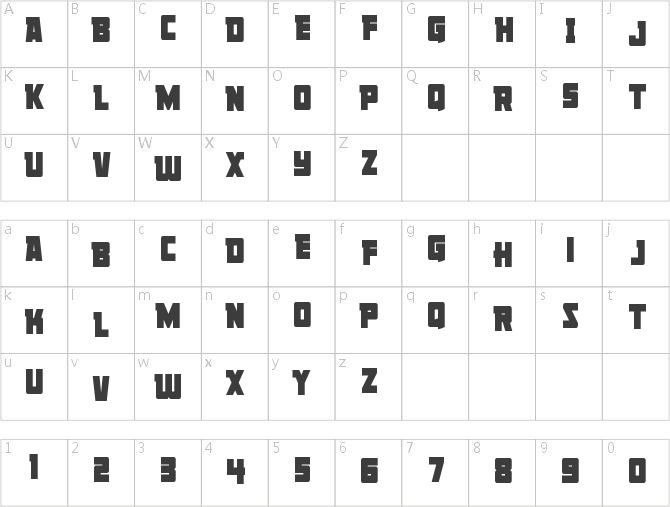
libertylegioncond 詳情頁
字體名稱: liberty
libertylegioncond
libertylegioncond字體字庫是一款讓人賞心悅目、百看不厭的英文字體,適合各類廣告和產品包裝設計應用,字體大小0.02MB,格式為ttf字體,上傳用戶是82年的拉菲,作者/版權方為未知